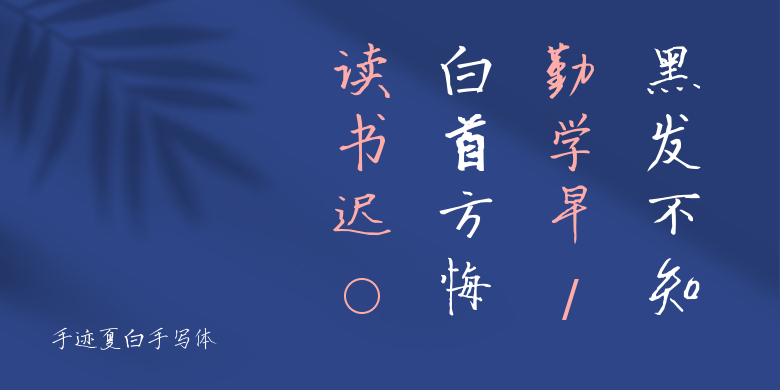
手迹夏白手写体
手迹夏白手写体,这款字体结构工整、笔画清晰,兼顾美观与易读性,适用于标题、正文、海报、包装、LOGO 等多种场景。字形优雅稳定,风格百搭耐看,适配日常排版与创意设计,让文字呈现更舒适、更具质感。手迹夏白手写体一笔一画,皆是细节,以均衡的比例、流畅的线条打造舒适视觉体验,字形端正大气,风格简约现代。无论是商业设计、品牌宣传还是日常排版,都能轻松驾驭,让文字更有格调与力量。手迹夏白手写体字体下载。